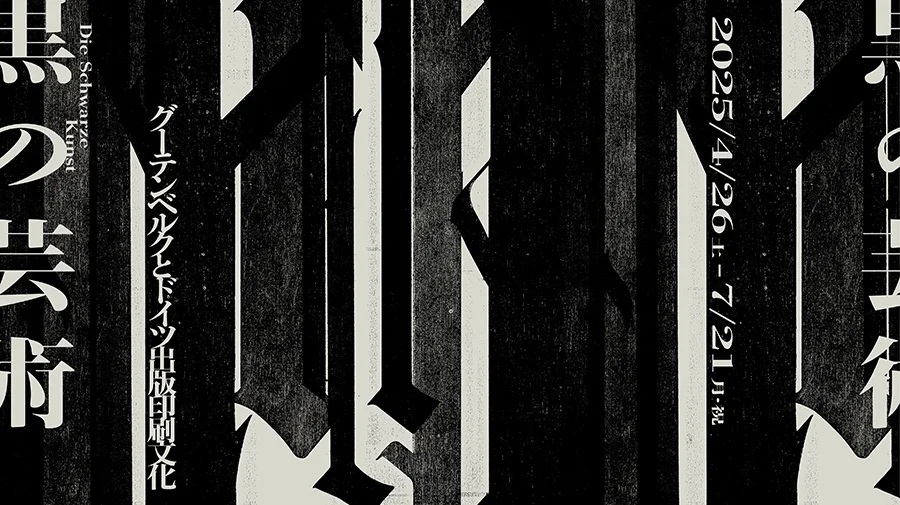
Monotype 、TOPPANホールディングス株式会社 印刷博物館 企画展 「黒の芸術 グーテンベルクとドイツ出版印刷文化」に協力
米国Monotype Imaging Inc.の日本法人Monotype株式会社(東京都港区、以下Monotype)は、TOPPANホールディングス株式会社(本社:東京都文京区、代表取締役社長CEO:麿 秀晴)が運営する 印刷博物館の企画展「黒の芸術 グーテンベルクとドイツ出版印刷文化」展において、ドイツ在住のクリエイティブ・タイプディレクター 小林章のトークイベントが開催されます。
また本企画展の図録へ、ドイツ出身のタイプフェイスデザインディレクター ヨアヒム・ミュラー・ランセイがブラックレターをテーマに寄稿したことをお知らせいたします。
※ブラックレター:ドイツで20世紀まで出版印刷に常用された書体
企画展 「黒の芸術 グーテンベルクとドイツ出版印刷文化」
2025年4月26日(土)から7月21日(月・祝)までの期間中、印刷博物館(東京都・文京区)にて開催。
西洋中世末期の15世紀半ば、ヨハネス・グーテンベルクが活版印刷術を完成させました。この印刷術は、テキストの複製手段が主に手写だったヨーロッパで瞬く間に広がり、以後約500年にわたり、文字印刷の主流であり続けました。 活版印刷術の発祥の地ドイツでは、この活版印刷術に魔術や魔法と同義のディ・シュヴァルツェ・クンスト(die schwarze Kunst)という名称が与えられ、独自の出版印刷文化が形成されました。 企画展「黒の芸術 グーテンベルクとドイツ出版印刷文化」では、今日では過去のものとされている活版印刷術と活字書体が国の文化形成に大きく影響を与えてきた様子を、ドイツの出版物を中心とした約70点の展示品とともに紹介されます。  |
オリジナル金属活字製作に関するトークイベント開催
図録「黒の芸術 グーテンベルクとドイツ出版印刷文化」へ寄稿
ドイツ出身でMonotypeのタイプフェイスデザインディレクターであるヨアヒム・ミュラー・ランセイが、図録への特別寄稿を行いました。「ブラックレターと私 —現代世界におけるブラックレター」と題して、自身の子ども時代から世界各国でカリグラファーや書体デザイナーとして活動した彼独自の視点を基に、ブラックレターについて解説しています。